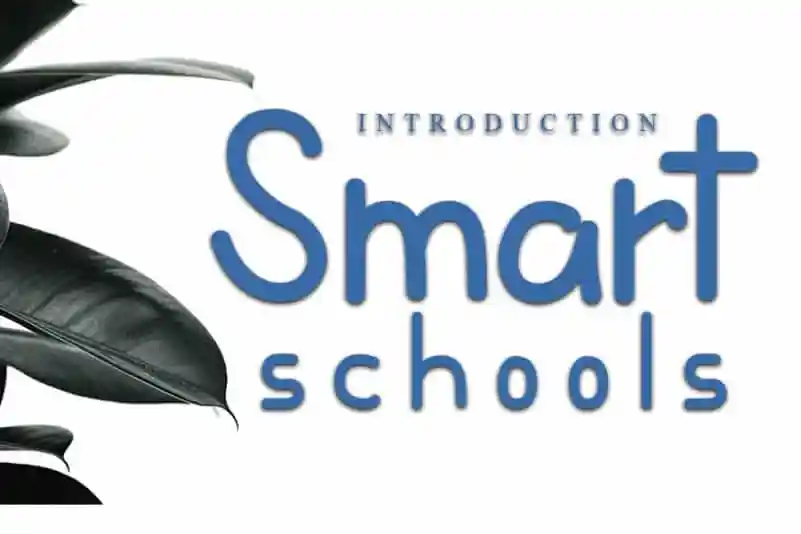
Smart School Display Font – Download Grátis
A Smart School Display Font é uma elegante fonte sem serif que transmite seriedade ao mesmo tempo que se move para atender às necessidades contemporâneas e frescas. Ela é perfeita tanto para letras de cartão ou títulos quanto para materiais de escritório, oferecendo um amplo espectro de aplicabilidades. Este tipo de fonte não só mantém seus elementos clássicos, mas também apresenta uma personalidade inovadora e atual que a torna perfeita para projetos criativos e divertidos. Ideal tanto para cartões de visita quanto para títulos, essa fonte oferece um grau de flexibilidade extremo. O seu design contemporâneo combina perfeitamente com elementos chamativos, tornando-a uma escolha sólida para ambientes de marketing ou comunicação social que buscam equilibrar o sofisticado e o descontraído. Sua simplicidade e elegância fazem dela um excelente candidato para criações gráficas variadas, desde materiais de escritório até cartões de fidelização, sempre mantendo seu ar cosmopolita. Ideal tanto para projetos profissionais quanto para iniciativas mais criativas, a Smart School Display Font é uma escolha sólida para designers que buscam um equilíbrio perfeito entre classe e modernidade. Sem dúvida, ela oferece aos criativos um poderoso aliado visual.